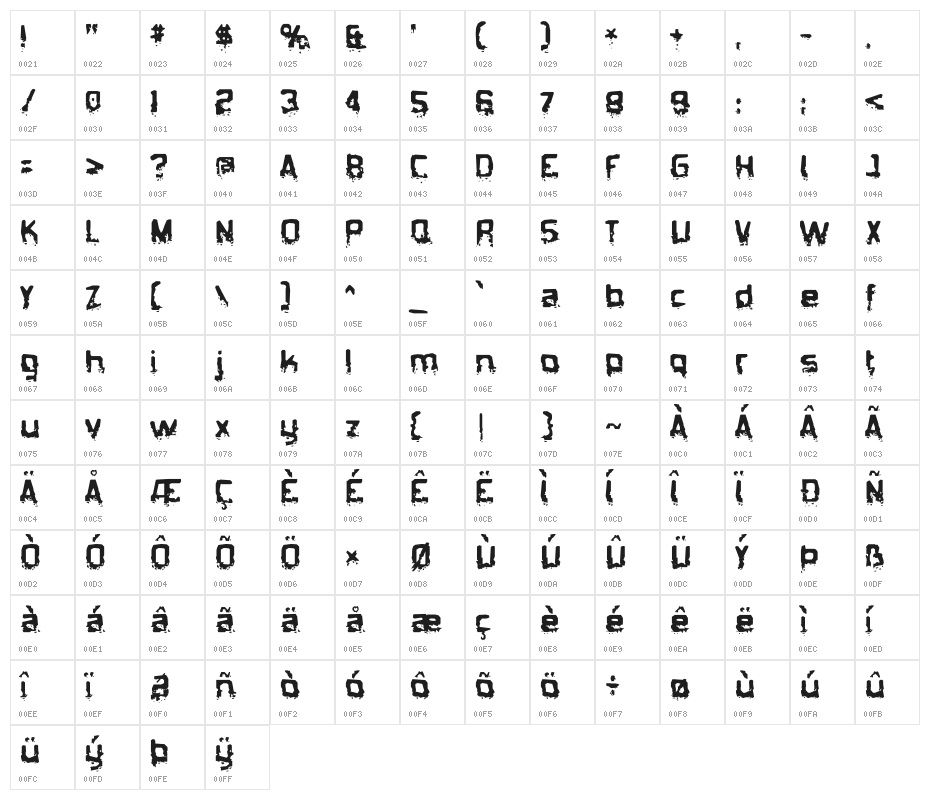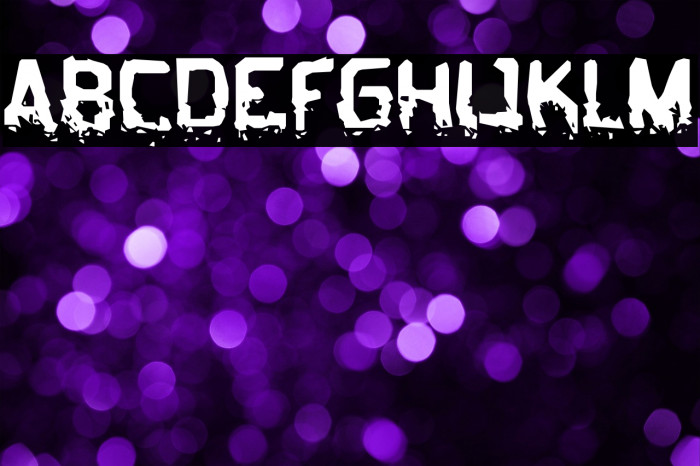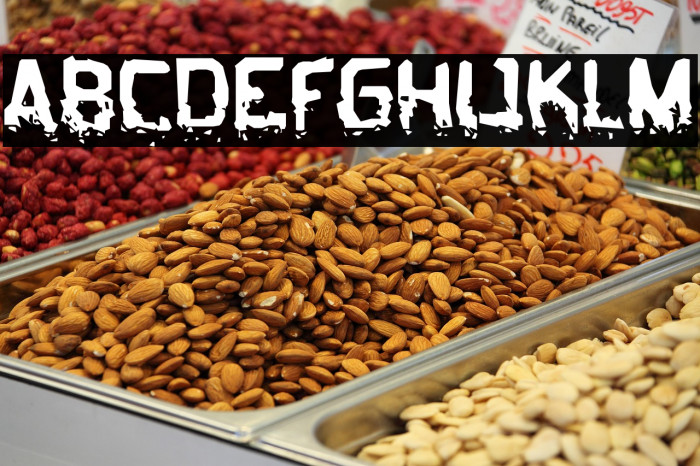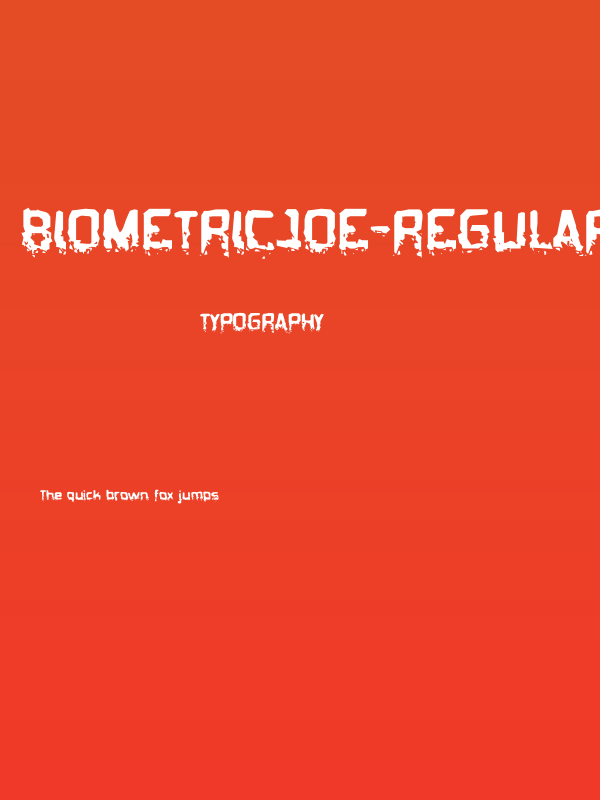
BiometricJoe-Regular Font
✎ Distorted Eroded
| Categorie | Distorted Eroded |
| Stile generale | Grunge, Distressed, Edgy |
| Progetti proposti | Album covers, posters, streetwear branding, skateboarding graphics, or any project needing a grunge or rebellious aesthetic. |